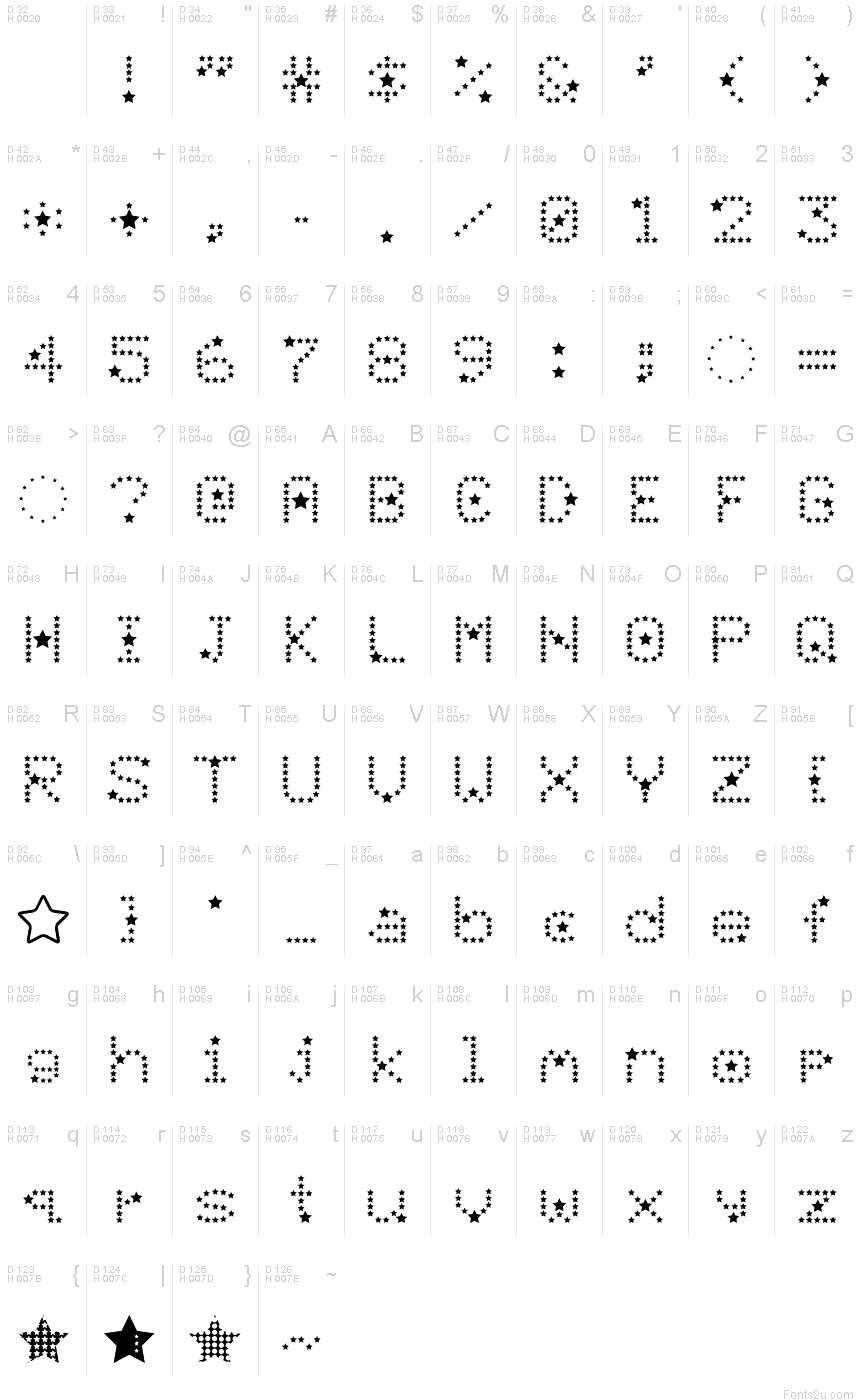
Divo di Tea Wat è un carattere decorativo gratuito che trasforma ogni parola in una scia di stelle audaci e inchiostrate. Ogni lettera è delineata da forme stellari nitide e spaziate uniformemente, conferendo al testo l'aspetto di un'insegna luminosa o di coriandoli sospesi a mezz'aria. È giocoso ma leggibile, con un ritmo chiaro che si legge facilmente nei corpi grandi, pur mantenendo un tocco divertente e leggermente teatrale.
Con il font Divo, puoi mettere titoli e loghi al centro della scena su inviti, copertine di libri per bambini, poster di festival, grafiche per i social, titoli di giochi e merchandising. Questo font gratuito brilla quando è grande e luminoso: provalo tutto in maiuscolo per il massimo impatto, quindi abbinalo a un sans serif geometrico pulito per il testo principale per mantenere il look nitido e leggibile.